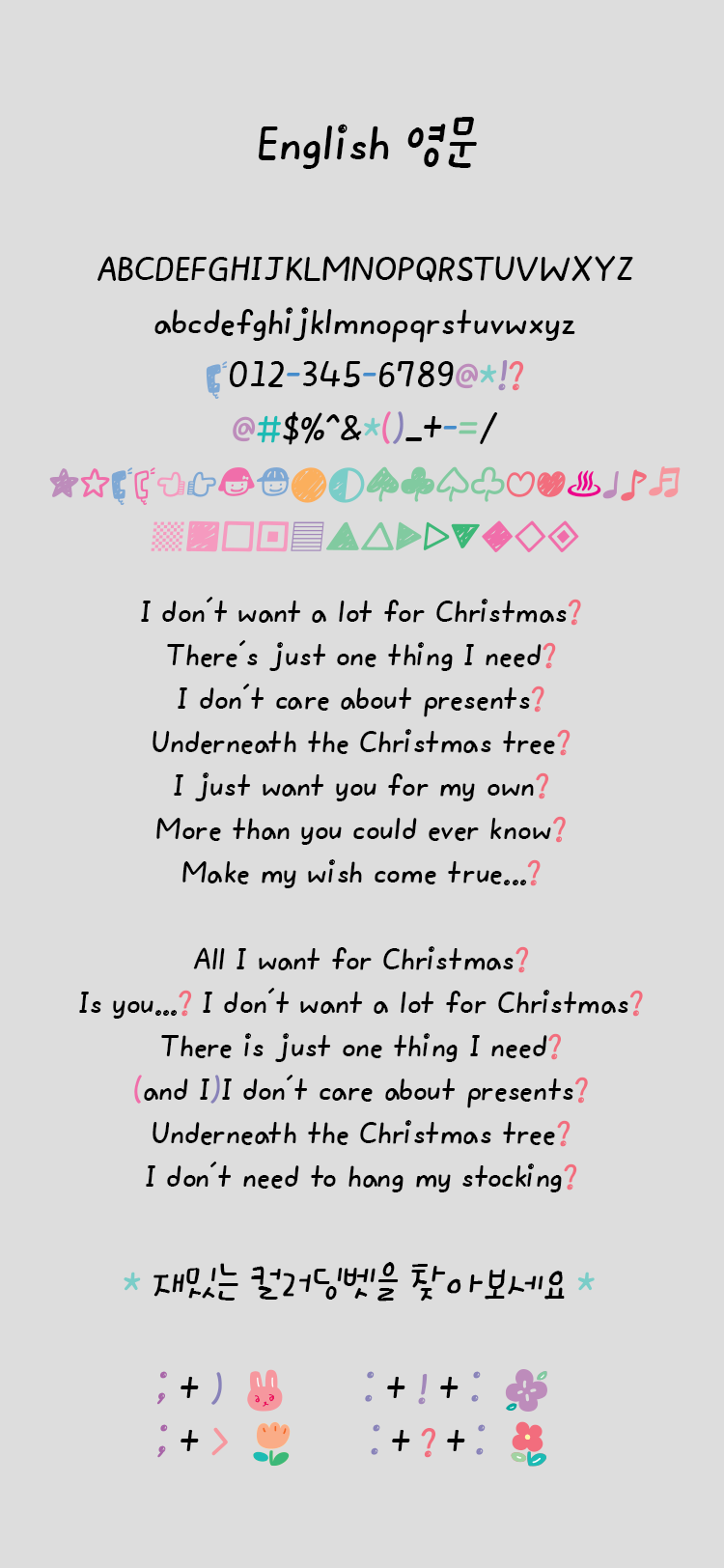
Ah 그림같은날이야
[Ah그림같은날이야]은 자소들을 삐뚤빼뚤 서툴지만 정성스럽게 써내려간 Ah폰트 느낌의 폰트로
자연스러운 손글씨 형태가 특징입니다. 기울기를 살짝주어 편안하게 읽힐 수 있도록 하였고,
글줄은 중하단으로 설정하여 시각적으로 안정적이면서도 전체적인 자소 형태에 자유로운 재미를 더했습니다.
특별한 히든딩벳이 숨어져 있으니 찾아보시기 바랍니다. :>